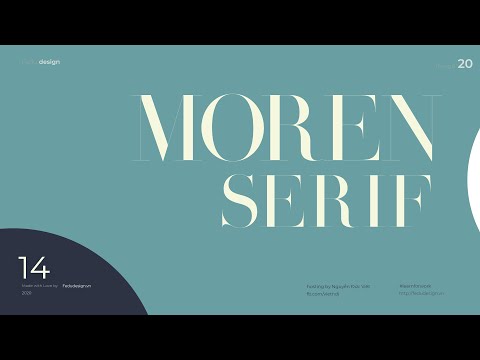
30 Font Chữ Làm Logo Tuyệt đẹp cho Dự án Thiết kế Thương hiệu của Bạn
Peace Sans là một font chữ đậm được tạo ra bởi niềm đam mê! Font này có thể giúp dòng chữ của bạn tạo cảm giác chứa chan lòng tốt và hòa bình. Peace Sans là font mang tính bổ trợ và có thể được sử dụn
Font thời trang đẹp Belove Font Belove với phong cách viết tay nghệ thuật, ổn cho các thiết kế như thơ từ, logo, ấn phẩm văn phòng,… Font hiện đại thời trang Allema Font Allema đầy nghệ thuật và mang
Oct 12, 2020Saonara là font chữ serif cổ điển được lấy cảm hứng từ các font chữ dành cho thời trang như Didot. Bộ font này những nét dày và mỏng được thiết kế dành cho những tiêu đề lớn hoặc logo, như
Font chữ này trông dày và đẹp khi được tô màu và phác thảo. Download ngay. Font chữ miễn phí 2020. ... Lấy cảm hứng từ thời trang, font chữ Saonara thực sự đáng nhớ với độ tương phản lớn giữa độ dày c
Aug 13, 2021Các bạn có thể xem những tấm hình demo cho bộ 70 font mà D3design sắp chia sẻ, bằng việc kết hợp với các texture giấy cũ và brush, dường như nó làm tôn vinh lên vẻ đẹp rất cổ điển của bộ f
Apr 26, 2022Top 4 thể loại font chữ và cách dùng trong thiết kế đồ họa (Phần 1) Apr 26 2022 Mục lục 1 Phông chữ Serif 1.1 Old Style Serifs 1.2 Transistional Serif 1.3 Didone Serif 1.4 Slab Serif 2 Các
Jan 27, 2022Font chữ chữ thảo này có một vẻ ngoài cao cấp. Hơn nữa, phần đuôi dài và xoáy cũng tạo thêm nét cá tính cho mặt chữ. Mặc dù font chữ logo này có vẻ hơi cách điệu, nhưng mỗi chữ cái vẫn khá
May 25, 2022Và đây chính là điểm nhấn tuyệt hảo cho các thiết kế cao cấp hoặc các bài viết về chủ đề thời trang, lối sống. 7. Zimra Serif Nếu bạn muốn một font chữ sang trọng thì Zimra sẽ đáp ứng mọi
Có thể nói rằng font chữ Kage Pro này có liên kết mật thiết với thiết kế thời trang Châu Âu và Toàn cầu, những thiết kế sử dụng font Kage Pro đều được đánh giá cao về sự linh hoạt, động đáo và sự phá
Elaris mang đến một sự thay đổi thú vị cho các font chữ serif thông thường . Nó là sự lựa chọn tuyệt vời cho các chủ đề thời trang và lối sống, mang đến vẻ đẹp thanh lịch thu hút sự chú ý của người xe
Jul 13, 2021Font chữ serif lấy cảm hứng thời trang này là một sự bổ sung tuyệt với cho bất kỳ bộ sưu tập font chữ nào tập trung vào việc tạo ra các tiêu đề hoặc thiết kế in ấn sáng tạo. Sự pha trộn gi
Thiết kế logo thời trang nữ ưu tiên những nét mềm mại, nữ tính, thể hiện sự thanh lịch và quyến rũ. Font chữ thường mỏng, được cách điệu. Màu sắc nhẹ nhàng, thường sử dụng tông sáng hoặc dùng những mà
Font chữ serif lấy cảm hứng thời trang này là một sự bổ sung tuyệt với cho bất kỳ bộ sưu tập font chữ nào tập trung vào việc tạo ra các tiêu đề hoặc thiết kế in ấn sáng tạo. Sự pha trộn giữa các nét d
Font chữ Cabana được thiết kế bởi Adrien Coquet này trông tuyệt vời trên đồ họa được trang trí với các đường vẽ tay thẳng. Mềm mại và tròn trịa, Cabana là một font chữ tròn tuyệt vời cho tất cả các lo
Loại phông chữ này thường được áp dụng cho các thương hiệu thời trang, mỹ phẩm và quảng cáo với nhằm mang lại cảm giác tự nhiên và tạo sự thích thú cho người xem. Nội dung bài viết [ ẩn] Share MIỄN PH
May 3, 2021Hôm nay mình sẽ chia sẻ cho các bạn một font thời trang cực kì xuất sắc, mang vẻ đẹp hiện đại nhưng cũng không kém phần duyên dáng, nhẹ nhàng. Đó chính là Display Catavalo Font. Mình giải t
Phù hợp với thiết kế logo thời trang, báo. Download tại Bēhance 06. Kolikö Fontfirma Font chữ Kolikö của Fontfirma có các ký tự Latin và Cyrillic theo phong cách thông thường, mỏng và đậm. Nó là một f
Feb 8, 2022Streetwear là một font chữ rất cá tính, mang đậm cảm hứng retro và đã làm ra một làn sóng rộng khắp trong giới thời trang và thiết kế trong những năm 1960 và 1970. phù hợp cho thiết kế logo
Calibri. Garamond. Bookman. Font chữ sử dụng cho website là yếu tố thường bị bỏ qua khi doanh nghiệp xây dựng web. Đây là điều không nên. Bất kể yếu tố nào hiển thị trên website cũng cần được lên kế h
Top font chữ không chân phổ biến nhất 2022 - Download trọn bộ font Sans Serif miễn phí cho các thiết kế siêu đẹp. Tham khảo ngay nhé. ... Font chữ này hợp thời trang, đơn giản, dễ nhìn, dễ đọc nhưng c
Font chữ phải lột tả được tính chất, cảm xúc cũng như thông điệp mà công ty, doanh nghiệp muốn truyền tải đến khách hàng của mình. ... Nhắc đến thời trang, bên cạnh những mẫu thiết kế tiêu biểu thì lo
14 font chữ viết tay tinh tế dành cho tờ rơi 1. Mightype là một font chữ viết tay được tạo bởi nhóm thiết kế chuyên nghiệp tại AF Studio. Font Mightype đơn giản và hoàn hảo cho thương hiệu lã
Cabana là font chữ được thiết kế bởi Adrien Coquet với dáng chữ cao cao, là sự lựa chọn tuyệt vời khi thiết kế trên đồ học trang trí. Cabana thực sự là một font chữ thú vị mà bạn nên thử. 6. Helvetica
Font chữ cho bao bì túi nilon shop thời trang. In trên túi nilon mở ra một thế giới toàn bộ các lựa chọn về kiểu in và phông chữ. Nói chung khi in lên túi ni lông shop thời trang, tốt nhất là in bằng
Ông lớn thời trang Calvin Klein cũng chọn font chữ này nhưng với nét mảnh mai hơn. 7. Ebay "Univers" thêm chút màu mè là thành ebay. 8. Instagram. Logo của Instagram viết bằng kiểu chữ bay bướm của "B
Jan 25, 2022Font chữ Thư Pháp là bộ font chữ làm chúng ta gợi nhớ đến thời xưa với những bức tranh thư pháp của các ông đồ. Font chữ thư pháp rất thích hợp cho các bạn làm thiết kế baner, thiệp, trang
Font chữ góp một phần không nhỏ trong hiệu quả thu hút người đọc, bạn đã hiểu font chữ cho trang web ? ... Cho dù website của bạn là một tạp chí online về thời trang hay blog của một nhiếp ảnh gia đi
Sep 25, 2021Streetwear là một font chữ rất cá tính, mang đậm cảm hứng retro và đã làm ra một làn sóng rộng khắp trong giới thời trang và thiết kế trong những năm 1960 và 1970. phù hợp cho thiết kế log